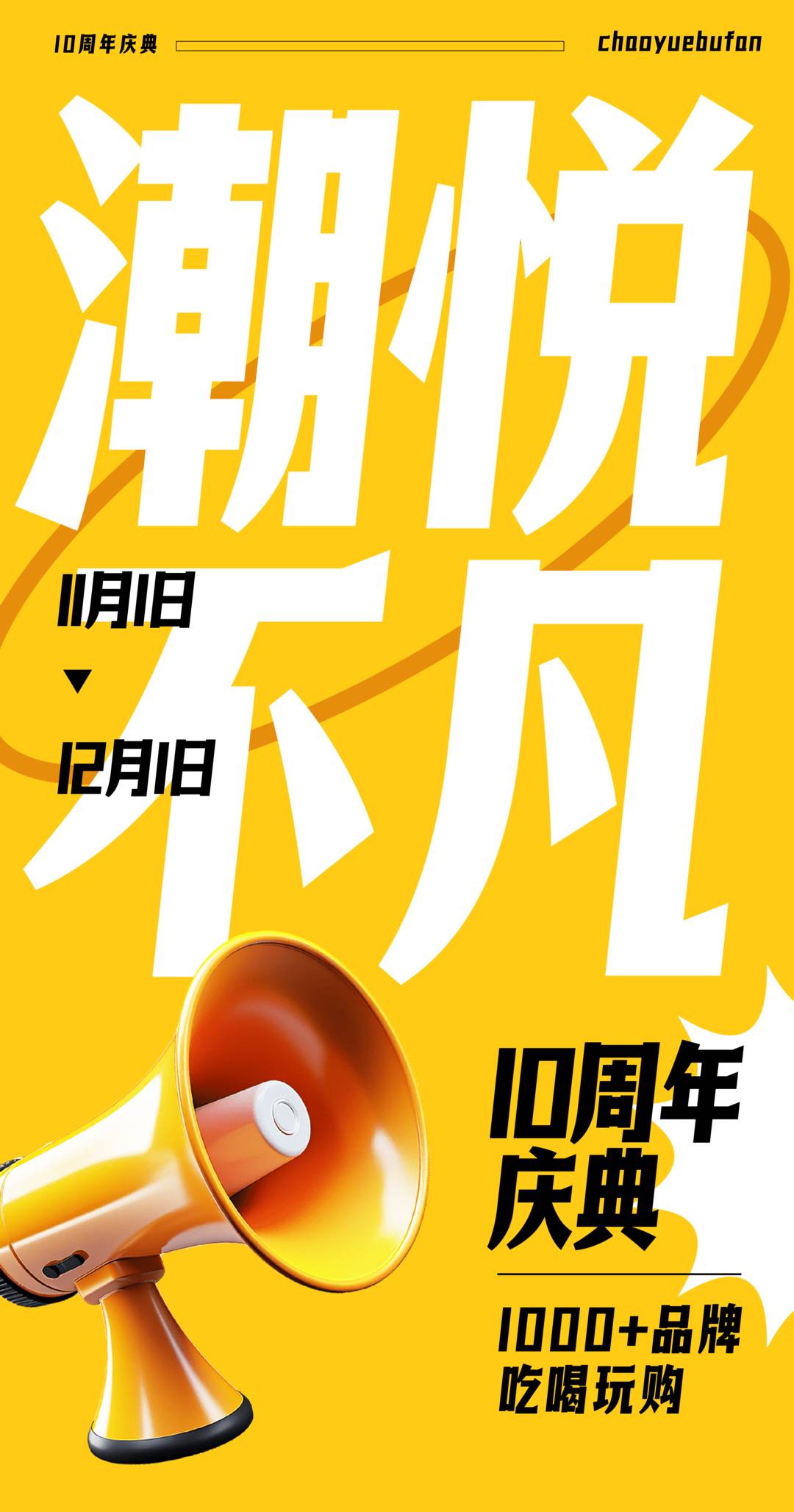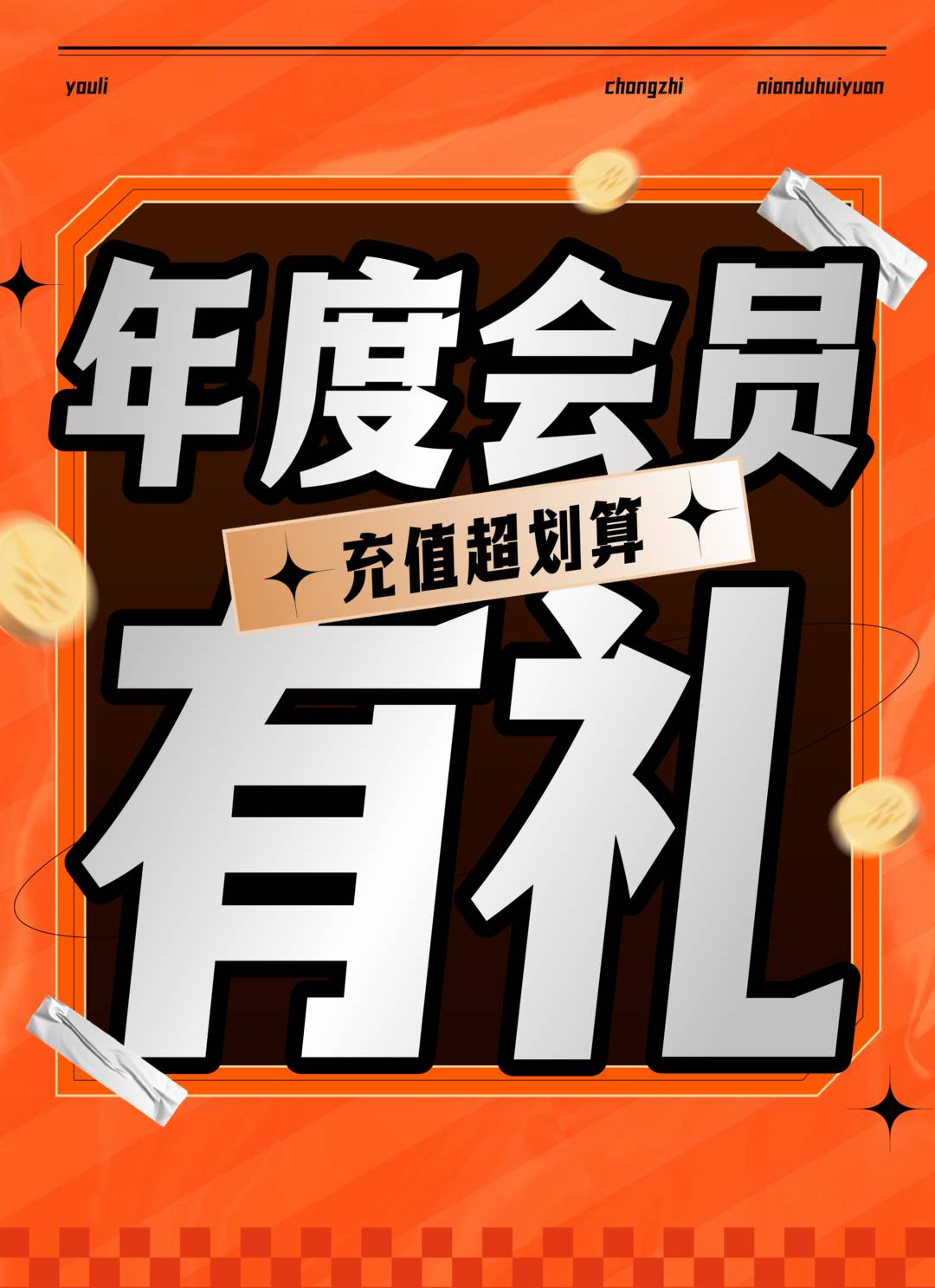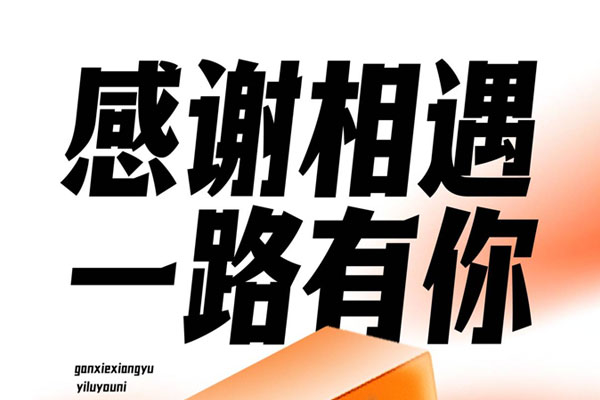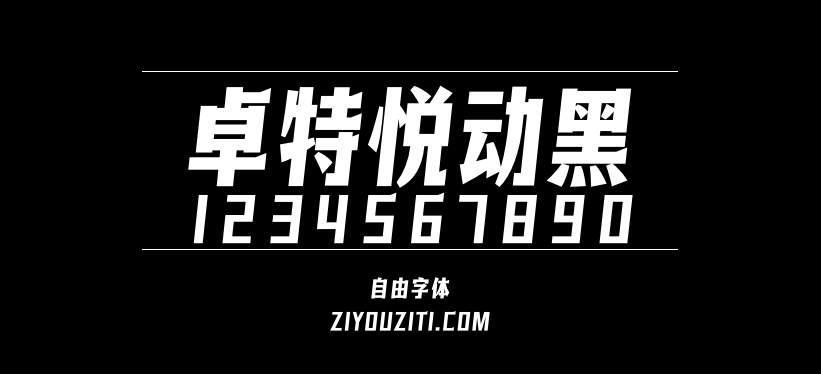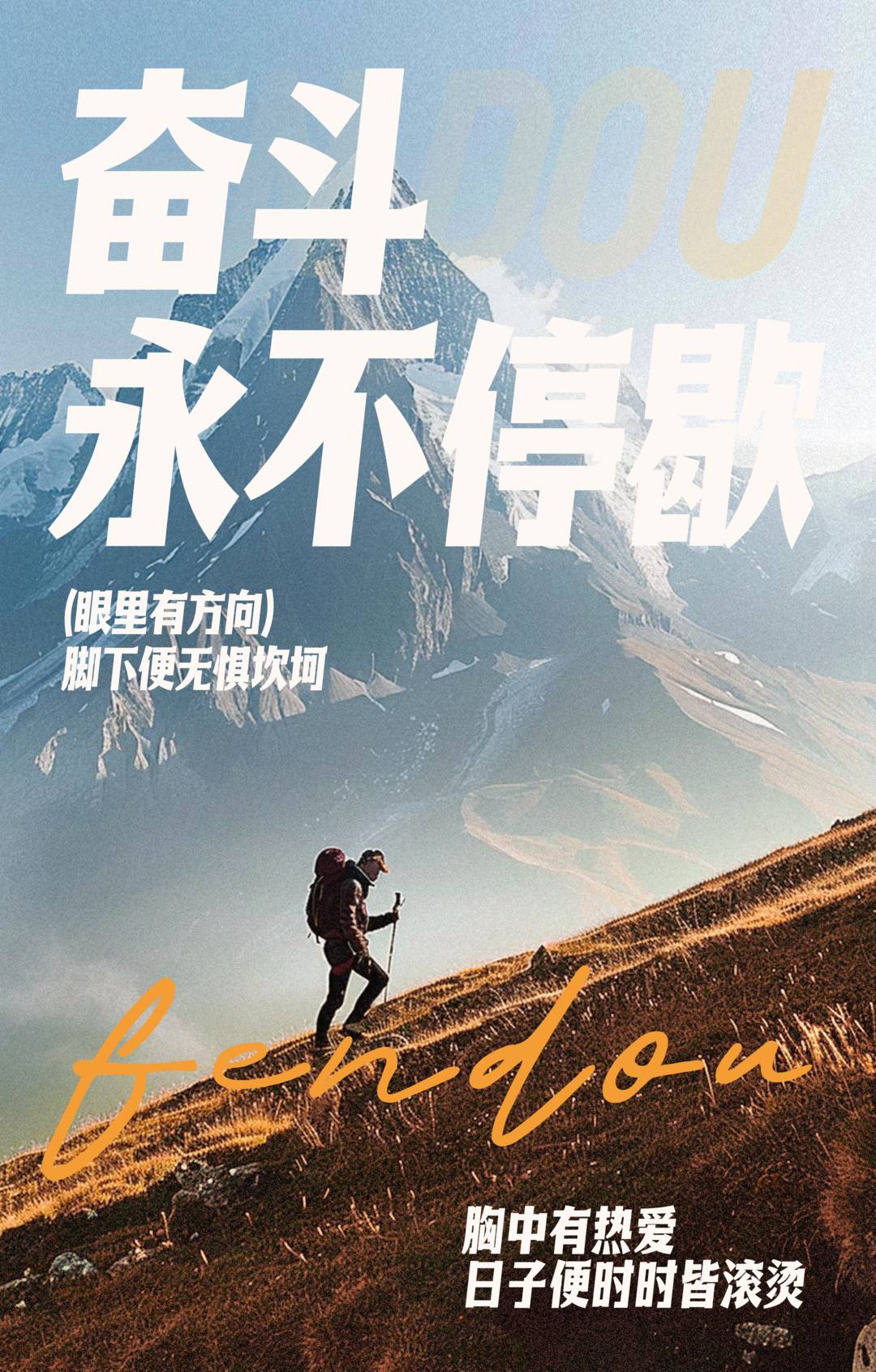
卓特悦动黑
卓特悦动黑字形高挑饱满,笔画厚实有力,富有强烈的力度感和动势。结合近代印刷美术字特征,横画外侧带有独特的尖角装饰。经自由字体检测,目前卓特悦动黑已覆盖GB2312规范的6763字,日常使用不会遇到缺字情况。
卓特悦动黑是一款由卓特视觉发布的开源简体中文字体,依据 SIL Open Font License 1.1(OFL)协议免费向公众开放使用。
本字体包含 GB2312-80 标准中的 6763 个简体汉字及 420 个常用字符,共收录 7183 个字符,可满足日常办公、设计创作、品牌宣传等多元场景的字体使用需求。